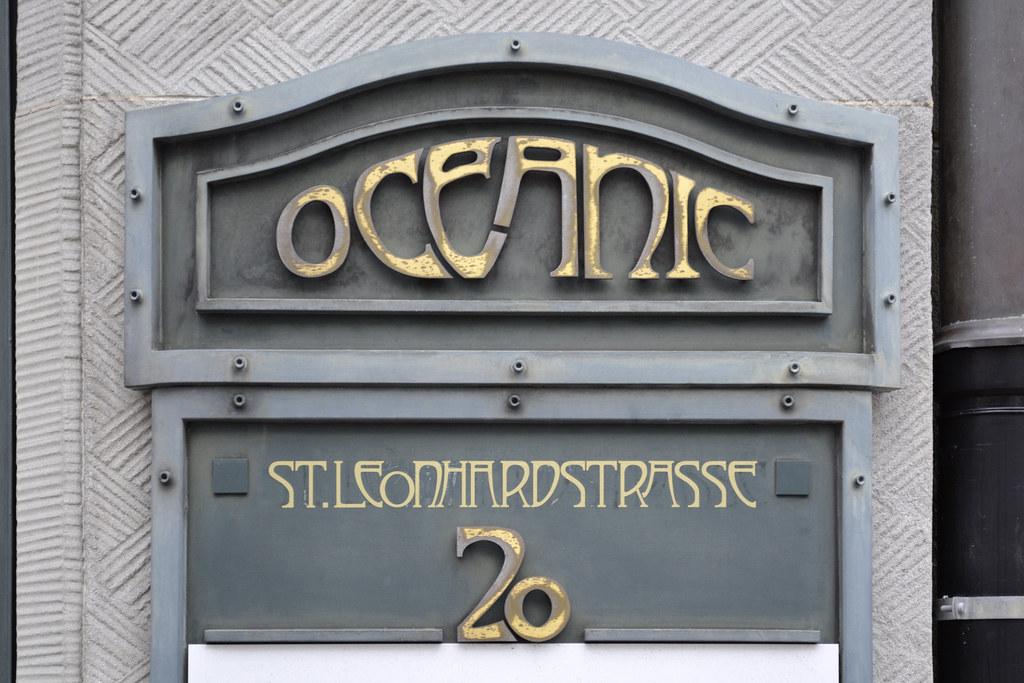
schrifft St. Leonhardstrasse
Hallo ich suche folgende schrifft von der St.Leonhardstrasse 20 in Sankt Gallen Schweiz
Schaut nach vordigitaler Entstehungszeit aus, dann mit größter Wahrscheinlichkeit keine benannte Schrift, sondern sorgfältige Grafiker/Schildermaler arbeit.
Kann man überhaupt von einer Ligatur sprechen? Die gibt es doch eigentlich nur im Satz, und gesetzt wurde das ja nicht.
Man könnte, wenn sich die Buchstaben berühren würden. Es muss irgendeine Verbindung da sein. Zwei Zeichen auf einem Kegel (berührend oder nicht) oder eben direkt verbunden bei Kalligrafie/Lettering.